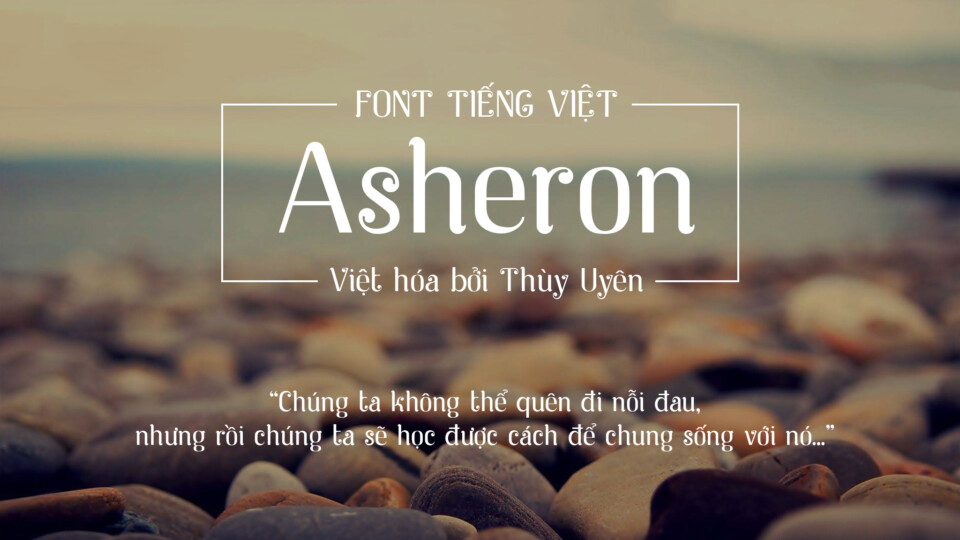
Font Việt hóa TUV Asheron II – Việt hóa bởi Thùy Uyên
Font Việt hóa TUV Asheron II – Việt hóa bởi Thùy Uyên: Nâng tầm thiết kế sáng tạo
Giới thiệu về Font Việt hóa TUV Asheron II – Việt hóa bởi Thùy Uyên
Trong thế giới thiết kế đồ họa, việc tìm kiếm một bộ Font Miễn Phí chất lượng cao và hỗ trợ đầy đủ tiếng Việt luôn là ưu tiên hàng đầu. Font Việt hóa TUV Asheron II – Việt hóa bởi Thùy Uyên là một trong những lựa chọn xuất sắc nhất dành cho cộng đồng designer Việt Nam. Với phong cách hiện đại, thanh lịch nhưng không kém phần mạnh mẽ, bộ phông này mang lại sự chuyên nghiệp cho mọi dự án từ văn phòng đến trường học. Sự tỉ mỉ trong quá trình Việt hóa của tác giả Thùy Uyên giúp các ký tự có dấu hiển thị mượt mà, tránh lỗi hiển thị văn bản thường gặp.
Đặc điểm nổi bật của Font Việt hóa TUV Asheron II – Việt hóa bởi Thùy Uyên
Thiết kế hiện đại và linh hoạt
TUV Asheron II sở hữu những đường nét hình khối dứt khoát, tạo cảm giác bền vững và tinh tế. Đây là công cụ đắc lực để thiết kế các ấn phẩm truyền thông, bài giảng điện tử hay báo cáo khoa học. Bộ phông này không chỉ đẹp về mặt thị giác mà còn đảm bảo tính dễ đọc trên nhiều thiết bị khác nhau.
Hỗ trợ tiếng Việt hoàn chỉnh
Ưu điểm lớn nhất của Font Việt hóa TUV Asheron II – Việt hóa bởi Thùy Uyên chính là hệ thống dấu câu được căn chỉnh chuẩn xác theo quy tắc ngôn ngữ Việt Nam. Điều này giúp các bạn học sinh và giáo viên dễ dàng soạn thảo tài liệu mà không lo bị lỗi font hay mất đi vẻ thẩm mỹ vốn có của bộ chữ gốc.
Ứng dụng và cách tải Font Việt hóa TUV Asheron II – Việt hóa bởi Thùy Uyên